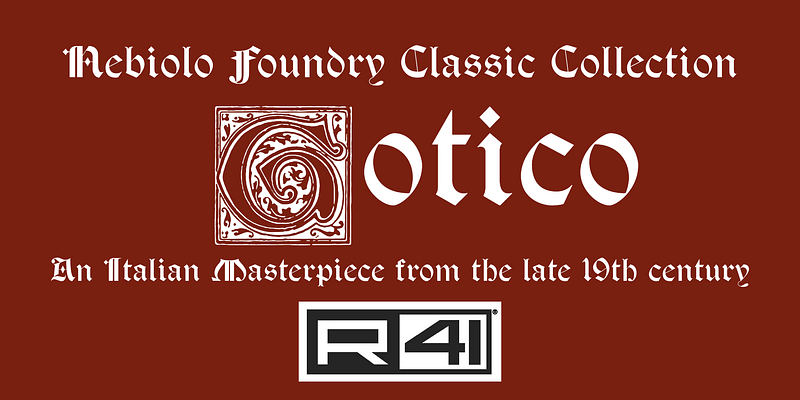
これは、19 世紀末にデザインされた Nebiolo 書体に由来しています。北欧起源のこのスタイルの書体は、中世のフランスで始まり、ドイツで国字として採用されました。当時の写本を通じてイタリアに輸入され、その後ドイツの印刷業者によってインキュナブラから輸入されました。その厳格なシェイプの際立った威厳に加えて、芸術的かつ装飾的な品質を備えています。
Aldo Novarese コレクション
トリノの伝説的な Nebiolo Foundry の最も象徴的なフォントはすべて、Aldo Novarese によってデザインされ、元のデザインに基づいてデジタル化され、完全に本物です。